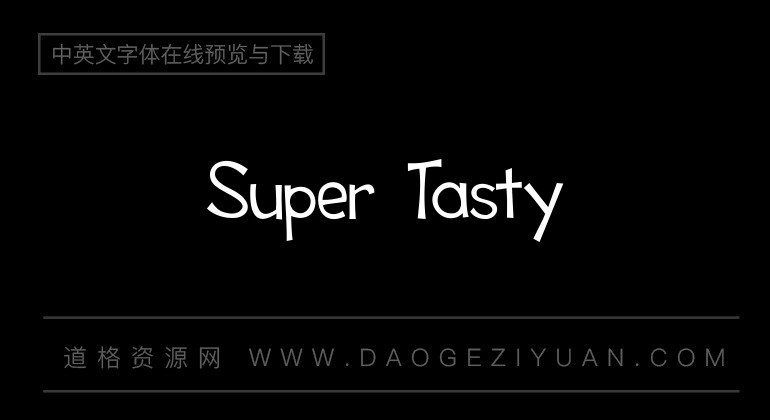
Super Tasty是一种手写风格的字体,具有非常明显的个性和独特的视觉效果。它的字母形状流畅而自然,有着浓郁的手写笔迹感。字体的设计带有一定的亲和力,适合用于设计卡通、标志、海报、包装、菜谱等应用场合。Super Tasty字体的最大特点是它独特的线条风格,看起来非常舒适和流畅。它的字母形状明快而清晰,使得阅读和识别文字非常容易。总之,Super Tasty字体是一种非常有趣和具有个性的字体,可以为设计带来一种活泼、轻松和可爱的氛围。内容介绍
Super Tasty是一款非常不错的手写艺术字体,具有很好的视觉感,适合于文化类的宣传设计、商业类品牌的广告和产品包装设计以及个性化文字排版等较多场景。